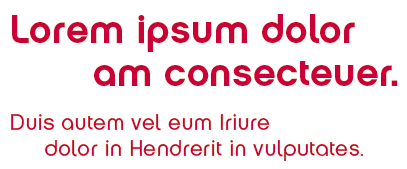
Ähnlich der Bauhaus - aber eben nur ähnlich
PS: Eben dachte ich es wäre die vermischten Lettern der Chalet New York 1960 und der Chalet New York 1970 - aber da stimmt dann das "i" noch immer nicht.
vielleicht ne chalet mit bauhaus i? oder eine angepasste variante?
ist das muster zufällig von airberlin? die nutzen auch die chalet mit anderem i punkt.
ggf. hat die chalet auch alternates.
Gibt es auch freie Schriften, die ähnlich sind wie die Chalet NY 1960? Ich bin totaler Amateur und möchte damit mal ein Logo ausprobieren. Vielleicht verwerf ich's auch wieder. Dafür sind $175 dann ein bisschen viel :-(
Wenn Du lediglich einen Logotext brauchst (der ja in der Regel sehr kurz ist), kannst du Dir das Wort auch bei den meisten Online-Schriftenhändler als Testtext anzeigen lassen und dann vielleicht bereits auf diese Weise beurteilen, ob die Schrift für Dich geeignet ist oder nicht. :-)